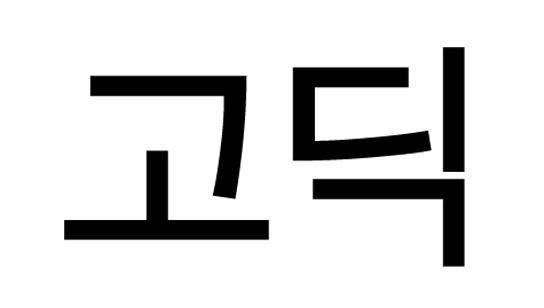
Sandoll 고딕
분류 Sans,민부리
종수 3종
본문용출판고전적
산돌 고딕은 기본 중의 기본 폰트로 본문에 가장 적합하게 디자인된 산돌의 스테디셀러이다.
산돌 명조와 마찬가지로 한글과 영문과 숫자 모두가 시각적으로 조화롭게 보이고 추가적인 수정이 필요없게끔 수많은 고민과 검토를 거쳐 제작하였다.
• 1995
• 이경배
• Sans,민부리
• Sandoll 고딕 / Sandoll Gothic